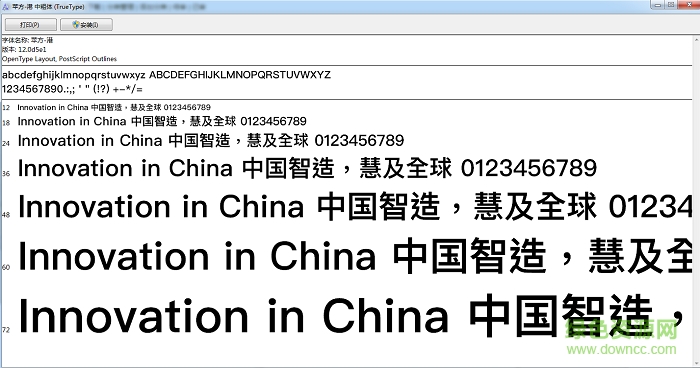
pingfanghk semibold字體
pingfanghk semibold字體又叫蘋方-港 中粗體,是一款字型規(guī)整大氣的蘋方字體,這款字體常常用在ios系統(tǒng)上,使用效果不錯,算得上是UI設(shè)計師必備的一款設(shè)計字體了,需要的朋友快來老師資源網(wǎng)下載吧?!